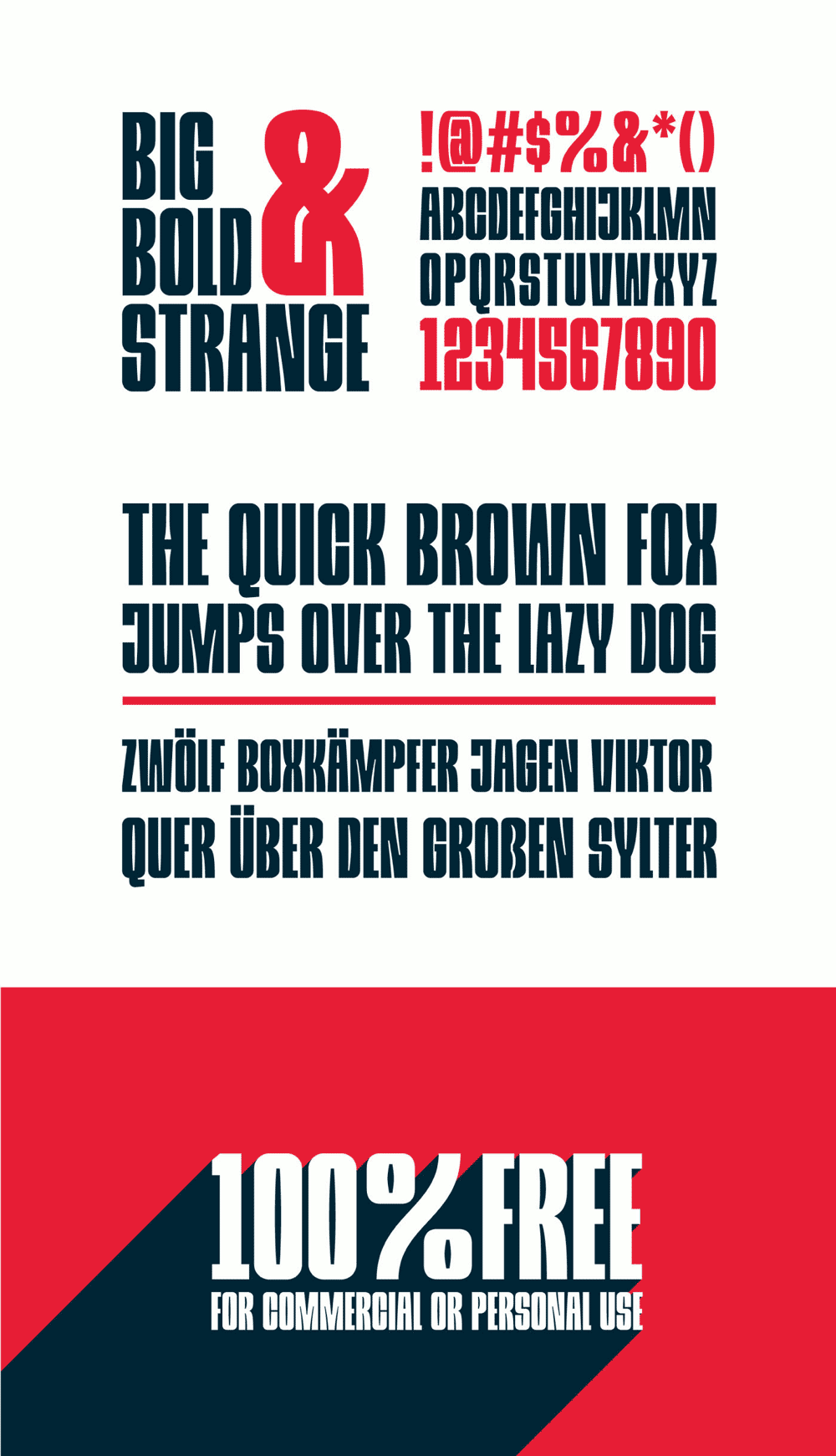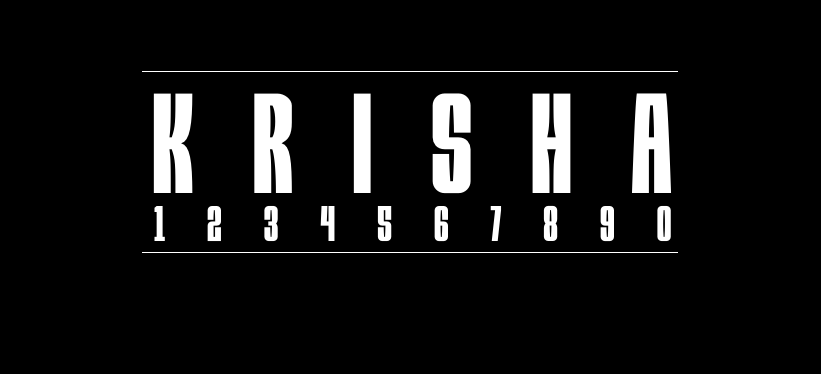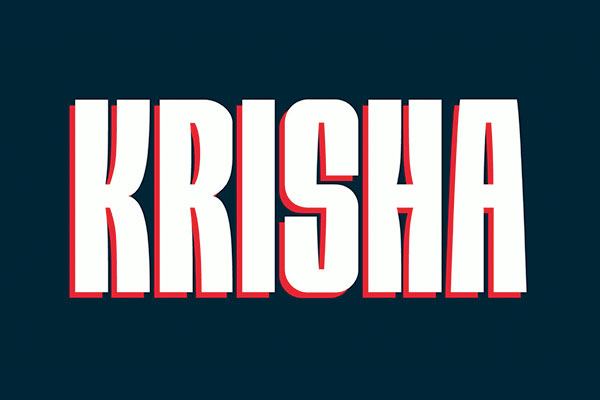
KRISHA是美国设计师 Daler Mukhiddinov创作的一款英文字体,KRISHA拥有大粗体英文字形,适合用于海报、标题等场合。
KRISHAd的字母部分全部都是大写显示字体。字符包含大写字母,数字,符号,并且是多语言的。Krisha非常适合使任何所需的项目脱颖而出,它非常适合于海报,标题,标题,服装等。